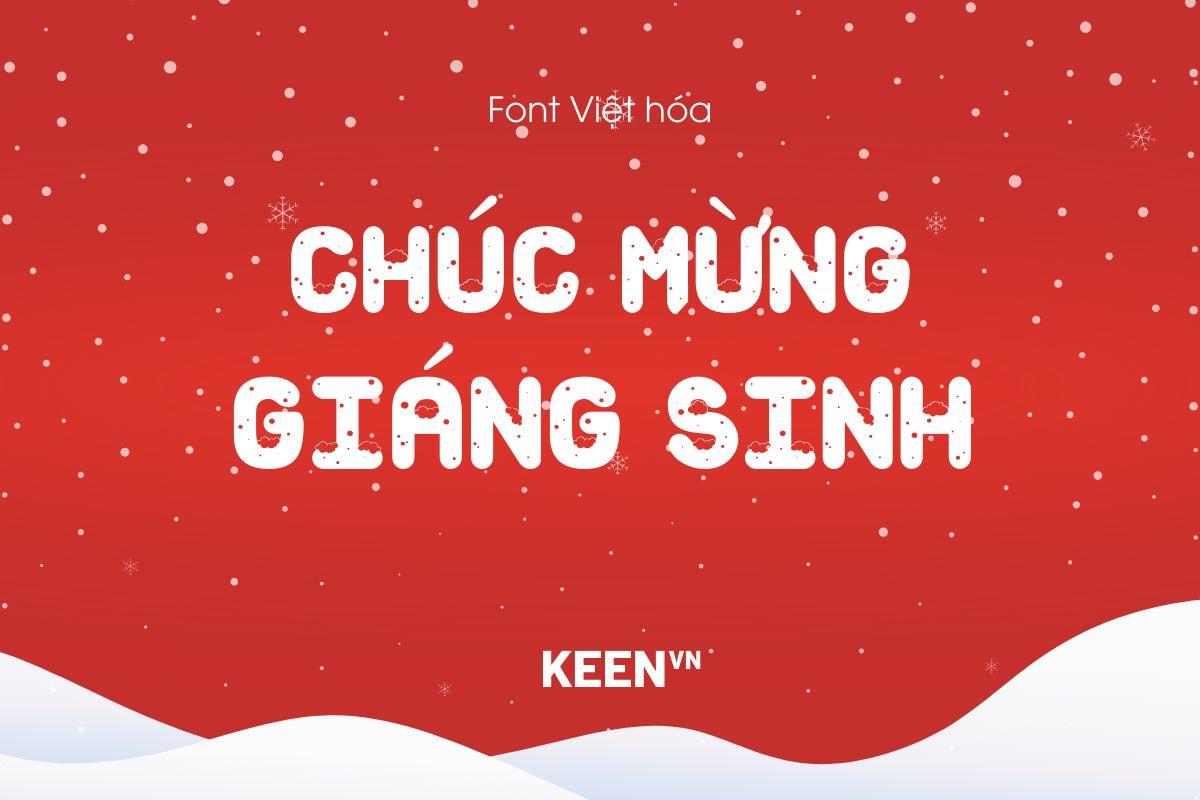
Font Việt hóa MTD Snow For Santa mang theo tinh thần Giáng Sinh dịu dàng và ấm áp, như những bông tuyết đầu mùa khẽ rơi xuống và phủ lên thiết kế một lớp phép màu ngọt ngào. Với cảm hứng từ sự diệu kỳ của mùa lễ hội, từng ký tự trong bộ font mang nét mềm mại, duyên dáng và lấp lánh, tạo nên phong thái mơ mộng rất riêng. Phiên bản Việt hóa được thực hiện tỉ mỉ giúp các dấu tiếng Việt hòa quyện hoàn hảo vào cấu trúc chữ, giữ trọn vẻ thanh thoát và hài hòa vốn có của font gốc, khiến Snow For Santa trở thành lựa chọn gần gũi và dễ sử dụng cho cộng đồng thiết kế Việt.
Phong cách của MTD Snow For Santa đặc biệt phù hợp với những dự án cần truyền tải cảm giác ấm áp, vui tươi và hơi thở mùa đông. Từ thiệp mời Giáng Sinh, bộ nhận diện mùa lễ hội, bao bì quà tặng, đến poster, banner truyền thông hay các ấn phẩm trang trí cửa hàng… font đều mang đến một không khí lung linh và thân thiện. Mỗi chữ cái xuất hiện như một chi tiết trang trí nhỏ, khiến tổng thể thiết kế thêm phần sống động và đậm chất lễ hội.
Sử dụng Snow For Santa không chỉ giúp bạn tạo ra những sản phẩm mang sắc thái Giáng Sinh rõ nét mà còn đem đến cảm giác hạnh phúc, ấm cúng cho người xem. Bộ font thể hiện được sự tinh tế trong từng đường nét, đồng thời khơi gợi nguồn cảm hứng cho những ai muốn tạo nên các thiết kế mùa đông thật đặc biệt. Nếu bạn đang tìm kiếm một kiểu chữ có khả năng tạo dấu ấn thị giác mạnh mẽ mà vẫn giữ được sự nhẹ nhàng và kỳ diệu, Font Việt hóa Snow For Santa chính là lựa chọn tuyệt vời để làm nổi bật tinh thần lễ hội trong mọi dự án sáng tạo.